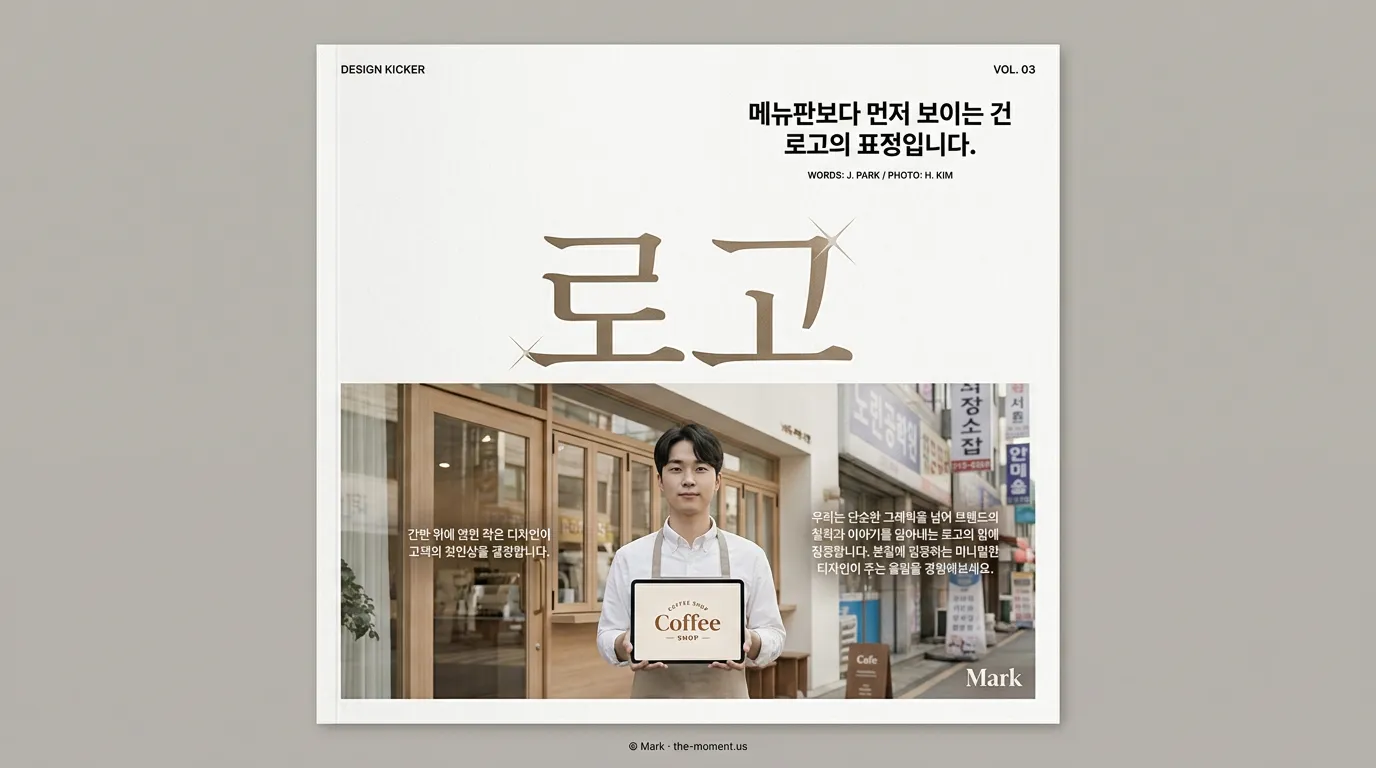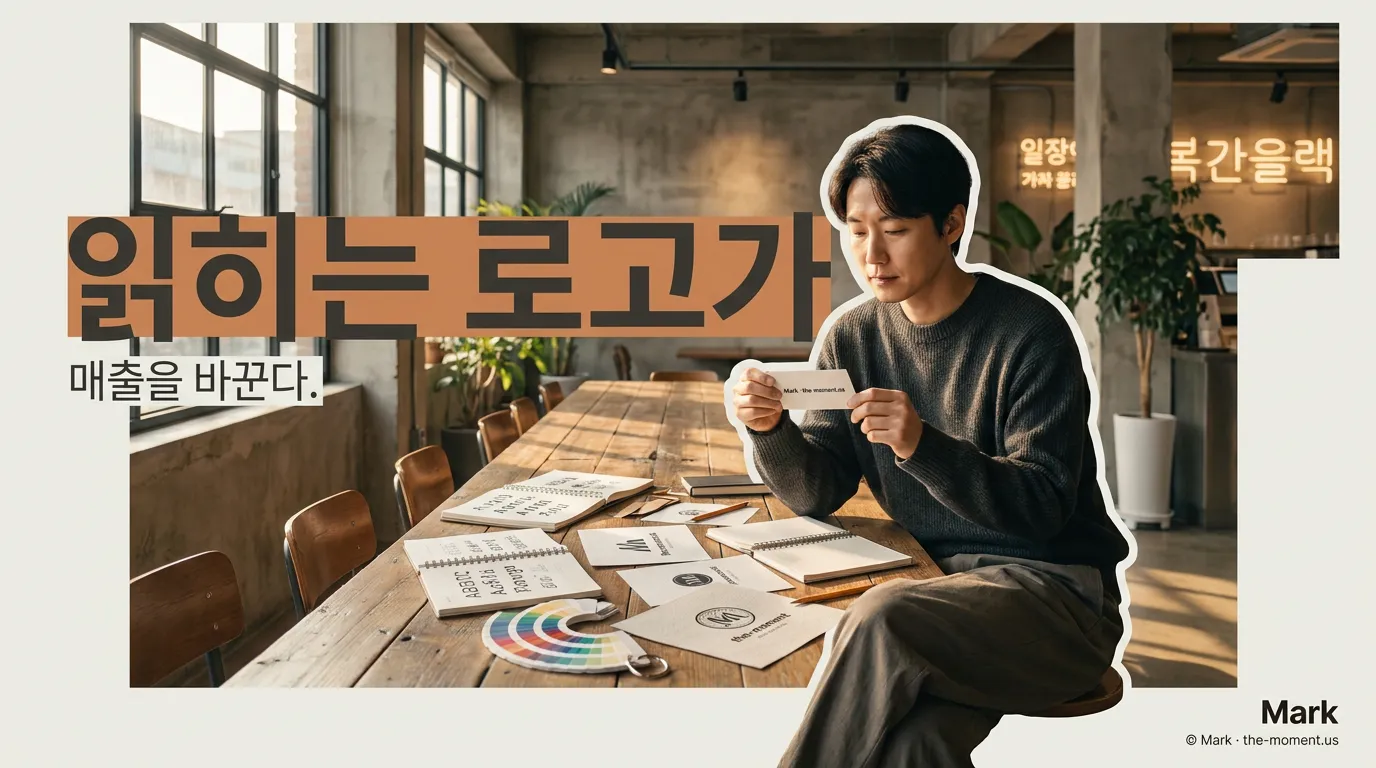
카페 간판 디자인, 매출 30% 문구보다 먼저 고쳐야 할 로고 색·폰트 3가지
카페 간판 디자인을 간판 제작이 아닌 로고·브랜드 아이덴티티 관점에서 다시 보는 색상·폰트 조합 가이드.
메뉴판보다 먼저 보이는 건 간판이 아니라, 간판 위에 얹힌 로고의 표정입니다.
왜 간판부터 만들면 로고가 흔들릴까요?
사장님이 처음 견적을 받을 때 제일 자주 듣는 말이 있습니다. “간판 크기는 이 정도, 조명은 채널로, 글자는 크게 가시죠.” 틀린 말은 아닙니다. 그런데 순서가 거꾸로입니다. 간판은 브랜드를 붙이는 자리이지, 브랜드 자체가 아닙니다.
저라면 먼저 로고를 잡습니다. 상호의 글자 모양, 심볼의 두께, 대표 색 하나, 보조 색 하나. 이 네 가지가 정리되지 않은 상태에서 간판을 만들면 컵, 스티커, 배달앱 썸네일, 인스타 프로필이 전부 따로 놉니다. 손님은 같은 카페를 여러 번 봐도 머릿속에 저장하지 못합니다.
최근 조선비즈 보도에서도 커피숍 수가 통계 작성 이후 처음 감소했다는 흐름을 짚었습니다. 원두값과 경기 문제도 있지만, 저는 여기서 한 가지를 더 봅니다. 이제 카페는 ‘예쁘다’만으로 버티기 어렵습니다. 멀리서도 한 번에 구분되는 자기 얼굴이 있어야 합니다. (biz.chosun.com)
색상은 예쁜 색보다 ‘기억되는 한 색’이 먼저 아닐까요?
카페 색을 고를 때 가장 많이 빠지는 함정이 있습니다. 요즘 감성이라는 이유로 크림, 베이지, 우드톤을 그대로 따라가는 겁니다. 문제는 골목 전체가 같은 색이 되는 순간입니다. 예쁜데 안 남습니다.
권유는 단순합니다. 대표 색은 하나만 먼저 정하세요. 말차를 파는 카페라고 무조건 초록, 디저트 카페라고 무조건 분홍으로 가라는 뜻이 아닙니다. 오히려 맛, 가격대, 공간의 온도를 한 단어로 정한 뒤 색을 붙여야 합니다. ‘조용한 작업 카페’라면 낮은 채도의 네이비나 그레이그린이 맞을 수 있고, ‘테이크아웃 회전이 빠른 카페’라면 대비가 강한 원색 포인트가 더 낫습니다.
한국소비자원이 커피전문점 이용자를 조사한 자료에서 눈에 띄는 부분이 있습니다. 소비자는 가격만 보지 않고 브랜드의 태도와 활동까지 선택에 반영합니다. 그러니까 색은 장식이 아니라 “우리는 어떤 카페인가”를 압축하는 신호입니다. 저는 카페 로고를 만들 때 예쁜 팔레트보다 먼저, 손님이 3초 안에 떠올릴 단어를 정합니다. (hankyung.com)
폰트는 감성보다 읽히는 속도가 먼저 아닌가요?
간판에서 손님이 읽는 글자는 생각보다 적습니다. 지나가며 보는 사람은 상호 전체를 음미하지 않습니다. 첫 글자, 글자 덩어리, 색 대비만 훑고 지나갑니다. 그래서 손글씨 느낌 폰트를 무조건 크게 쓰면 오히려 손해가 납니다.
상호가 한글 3~5글자라면 자간을 넉넉히 두고, 획 끝이 과하게 장식된 서체는 피하는 편이 좋습니다. 영문 상호를 쓰고 싶다면 더 조심해야 합니다. 예쁜 영문 로고가 실제 골목에서는 ‘무슨 가게인지 모르는 표시’가 되는 경우가 많습니다.
제가 현장에서 보면 좋은 조합은 이렇습니다. 로고 타입은 개성을 주되, 간판의 보조 문구는 아주 담백한 고딕으로 갑니다. 예를 들면 상호는 부드러운 세리프 계열, 아래 ‘coffee · dessert’는 얇은 산세리프. 반대로 상호가 단단한 고딕이면 심볼이나 색에서 온도를 줍니다. 폰트 둘이 같이 소리치면 브랜드가 피곤해집니다.
카페 컵, 외부 사인, 인스타 프로필에 같은 로고 색과 폰트가 반복 적용된 장면
심볼은 꼭 있어야 할까요, 아니면 이름만으로 충분할까요?
모든 카페에 그림 심볼이 필요한 건 아닙니다. 상호가 짧고 발음이 좋다면 글자 로고만으로도 충분합니다. 반대로 이름이 길거나 비슷한 이름이 많은 상권이라면 작은 심볼 하나가 기억의 손잡이가 됩니다.
여기서 심볼을 커피잔, 원두, 스팀으로 바로 가면 위험합니다. 이미 너무 많습니다. 손님이 기억하는 건 ‘커피를 판다’가 아니라 ‘저기 그 동그란 달 로고 카페’, ‘파란 리본 붙은 카페’ 같은 식입니다. 업종 설명보다 구분 장치가 먼저입니다.
마크에서 카페 로고를 잡을 때도 간판 파일부터 열지 않습니다. 작은 원형 스티커에 넣어도 보이는지, 컵 홀더에 찍혀도 무너지지 않는지, 네이버 지도 썸네일에서 읽히는지 먼저 봅니다. 그 다음에 외부 사인에 어떻게 얹을지 정합니다. 간판은 마지막 적용처입니다.
그럼 카페 간판 디자인은 어디까지 신경 쓰면 될까요?
간판 자체를 무시하자는 말이 아닙니다. 다만 순서를 바꾸자는 겁니다. 로고가 먼저고, 간판은 그 로고가 가장 잘 보이는 무대여야 합니다.
체크할 것은 세 가지면 충분합니다. 첫째, 배경색과 로고색의 명도 차이가 확실한가. 둘째, 낮과 밤에 같은 인상으로 보이는가. 셋째, 간판에 넣고 싶은 말을 덜어냈는가. ‘스페셜티 커피, 수제 디저트, 브런치, 포장 가능’까지 다 올리면 아무것도 남지 않습니다.
매출 30%를 색상과 폰트만으로 약속하는 말은 조심해야 합니다. 대신 로고가 정리되면 손님이 덜 헷갈립니다. 처음 본 사람은 들어올 이유를 빨리 찾고, 한 번 온 사람은 다시 찾기 쉬워집니다. 카페 브랜딩에서 이 차이는 꽤 큽니다.
지금 할 일은 하나입니다. 간판 견적서 보기 전에, 내 카페 로고를 스마트폰 화면 3cm 크기로 줄여도 읽히는지 먼저 확인하세요.